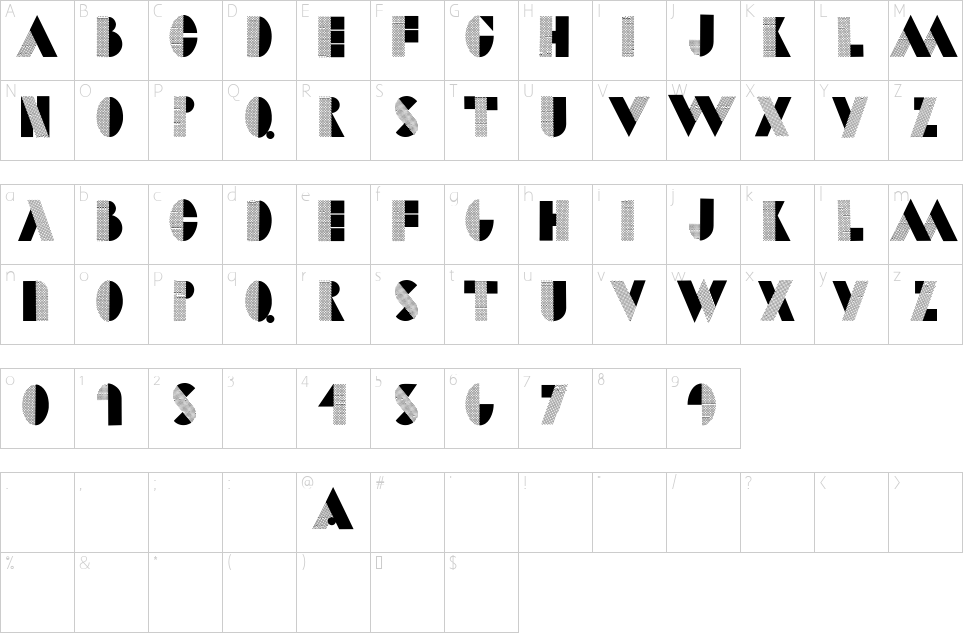
Descubra a sofisticação do Dot Caps MK Font para seus projetos digitais com esta categoria gratuita, especialmente idealizada para designers e entusiastas de design gráfico. O Dot Caps MK é uma tipografia única, criada por Manfred Klein, que oferece um toque elegante nas suas criações visuais. Esta fonte foi concebida para proporcionar um estilo único em qualquer projeto, sejam eles sites, relatórios ou até mesmo mensagens pessoais enviadas no seu e-mail. Dot Caps MK é uma escolha inteligente para quem busca adicionar um elemento de destaque ao seu design sem abandonar a legibilidade essencial. Com uma maneira cuidadosa de destacar letras e símbolos, essa fonte oferece um toque moderno que pode se adaptar tanto a projetos profissionais quanto pessoais. A opção de acesso à esta fonte do Windows e Mac torna ainda mais conveniente o uso desta tipografia incrivelmente única. Se você está procurando por uma fonte moderna e elegante sem ter que gastar muito, o Dot Caps MK é uma ótima escolha. Não espere mais para experimentar a diferença de adicionar esta arte gráfica a seus projetos!